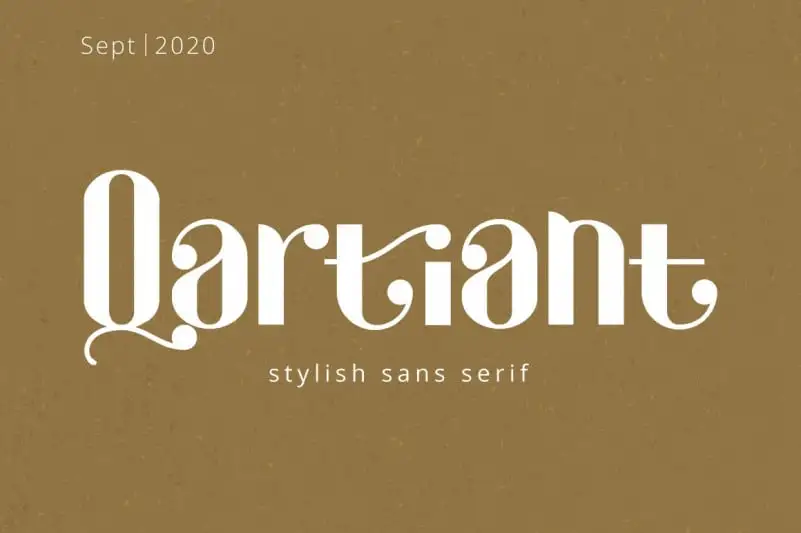
Qartiant Sans Serif Font – Download Grátis
A Qartiant Sans Serif Font é uma elegante tipografia sans serif com características femininas e glamurosas. Ela surge do trabalho genial de Attype Studio, apresentando a pureza do design minimalista num embuste de luxo exuberante. Esta fonte sans-serif oferece um toque refinado às suas composições, combinando elegância com uma dose de glamour. Suas linhas claras e precisas garantem que qualquer texto impresso ou digital seja sempre bem formado e profissionalmente apresentado. Ideal para anúncios publicitários, materiais de marketing, logos e design gráfico contemporâneo, a Qartiant Sans Serif Font é uma escolha perfeita para quem procura um equilíbrio entre modernidade e sofisticação.